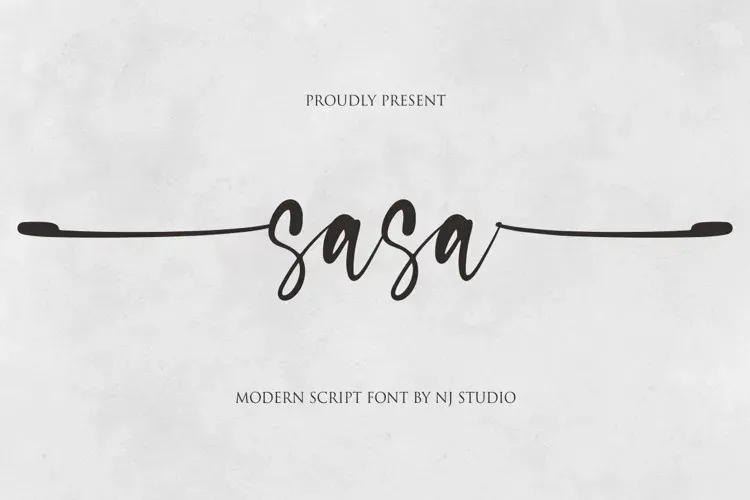
A fonte Sasa é uma elegante tipografia de script moderna criada pela NJ Studio com terminações arredondadas. Este tipo de letra traz aos seus projetos um toque sofisticado e contemporâneo, perfeito para criações gráficas variadas como cartões de aniversário, infográficos ou até mesmo design de blogs. Além das linhas curvadas e dos elementos arredondados que dão vida a sua tipografia, Sasa também inclui ligaturas que tornam suas letras ainda mais únicas e atraentes. Essas ligaturas permitem uma mistura inteligente de diferentes partes da letra, criando um resultado visualmente intrigante que certamente impressionará seus leitores e clientes. Se você está procurando por uma fonte script para dar vida a sua produção digital ou impressa, Sasa é definitivamente uma opção a ser considerada.